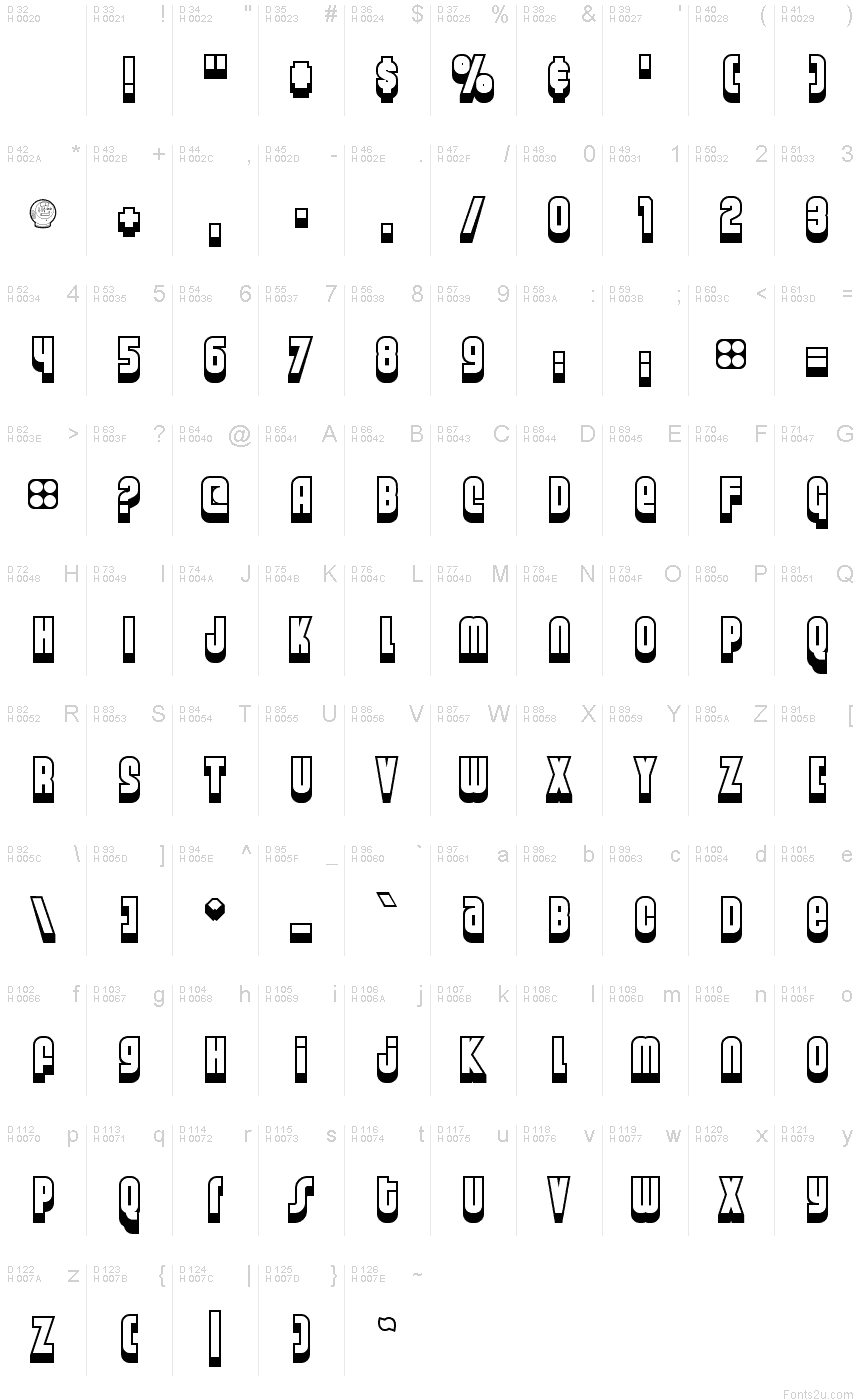
Podgląd czcionki Weltron 2001
Weltron 2001 od Weltron to darmowy font display 3D w stylu groovy, przesiąknięty klimatem pop późnych lat 70. Litery są przysadziste, zaokrąglone i ciasno upakowane, z łagodnymi rogami i ciężkim cieniem, który zamienia proste blokowe kształty w coś zabawnego, z nutką stylu space-age.
Naturalnie pasuje do retro logotypów, okładek płyt, nagłówków plakatów, brandingu w stylu arcade oraz plansz tytułowych, gdzie ten masywny cień szybko przyciąga uwagę. Jako darmowy font, Weltron 2001 sprawdza się również w przypadku krótkich napisów na opakowaniach czy wyrazistych cytatów, zwłaszcza gdy zależy Ci na ciepłym, plastikowym wyglądzie zamiast ostrego, geometrycznego wykończenia.